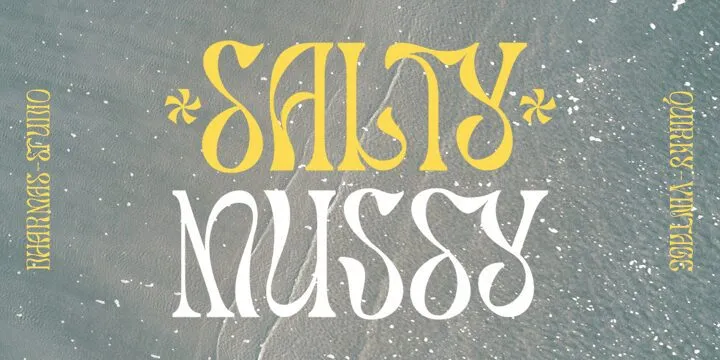
Salty Mussy Font
خط Twist Display جديد ، لذا هنا من أجلك ، Salty Mussy!
مالح موسي – محرف عرض ذو أسلوب ملتوي وملتوي ، يعيد أجواء السبعينيات بإيقاعه العصري ولكن غير التقليدي. يحتوي هذا الخط على أحرف كبيرة وصغيرة جميلة ، لذا يمكنه عرض المزيد من الخيارات لمشروعك!
Salty Mussy – يتم تضمين هذا الخط أيضًا في النمط المخدر والذي يمكن أن يكون مناسبًا جدًا للاستخدام في العديد من المشاريع مثل تصميم فن الشارع والملصقات والمجلات والاقتباسات لـ Instagram وغير ذلك الكثير!
حروف وأرقام وعلامات ترقيم ودعم متعدد اللغات
لديه 64 بدائل وأربطة جميلة